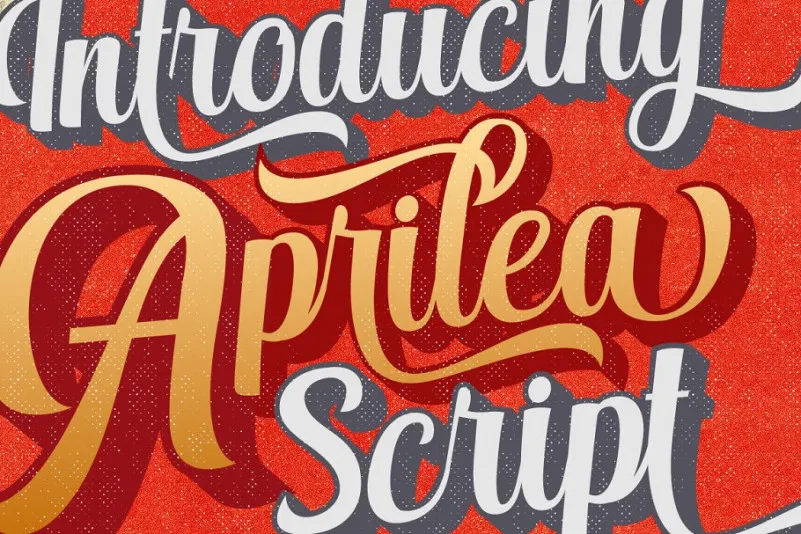
Estamos muito felizes por você estar olhando para esta nova linha de tipografias artesanal. Trabalhamos duro para criar uma fonte chamada Aprilea Script Font, que irá dar um toque especial ao seu design. Esta fonte é composta por duas opções: Regular e Extruded. Ambas as opções são capazes de gerar designs interessantes sem a necessidade de fazer alterações específicas no texto, o que significa que você pode focar mais em criar a sua arte, não na criação do efeito. Em uma era onde design está sempre buscando novos caminhos para se destacar, Aprilea Script Font foi concebida para designers jovens e entusiasmados. Ela é perfeita para aplicações como logomarcas, estampas de tênis, marcação e outros projetos de design diversos. Além disso, M.0Type, o designer responsável por Aprilea Script Font, trouxe uma nova maneira de tornar o texto singular e inovador, criando um universo de possibilidades para aqueles que buscam algo novo em seus designs. Em resumo, Aprilea Script Font é a fonte perfeita se você está procurando por uma maneira única e inspiradora de apresentar seu trabalho.